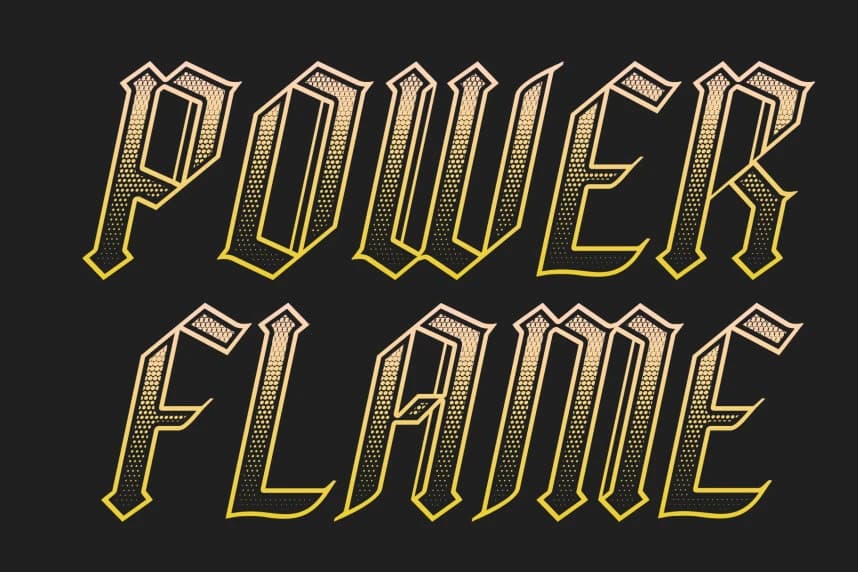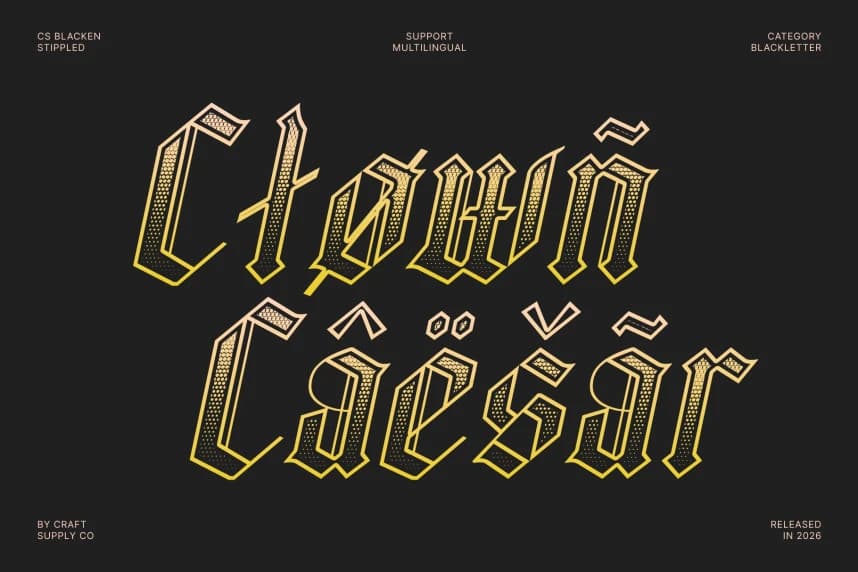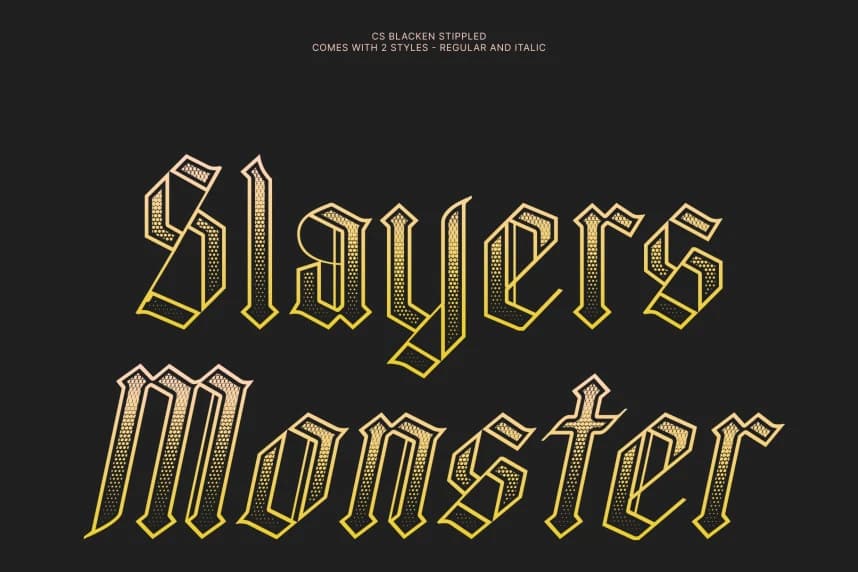
Sans Serif0CS Blacken Stippled Font – Asil Blackletter Yazı Tipi, Dokulu Görkeme Sahip. Tarihî Görkem, Gizemli Varlık Hissiyle. Bu, tarihî görkemi atmosferik bir gizem hissiyle birleştiren seçkin bir blackletter serif yazı tipidir.İndirmek için giriş yapDaha Fazla GörVarlık ÖzellikleriKategoriSans SerifLisans TürüKişisel LisansDosya TürüOtherDosya Boyutu71 KBCRcraftsupplyco@craftsupplycoKoleksiyona kaydetSayfa linkini kopyalaBildirAçıklamaCS Blacken Stippled Font – Dokulu Görkeme Sahip İhtişamlı Blackletter Yazı Tipi, Tarihî Görkeme Esrarlı Bir Varlıkla Birleşir. Bu, tarihî görkemi atmosferik bir gizem duygusuyla birleştiren seçkin bir Blackletter serif yazı tipidir.AAÖnizleme metin rengiSıfırlaCS Blacken Stippled1 fontCS Blacken StippledBunlar da ilgini çekebilir #Sans SerifKategoriyi görSans Serif12Goda FontSans Serif1Malisan Yazı Tipi AilesiSans Serif0Puffin Yazı TipiSans Serif0Scone Font